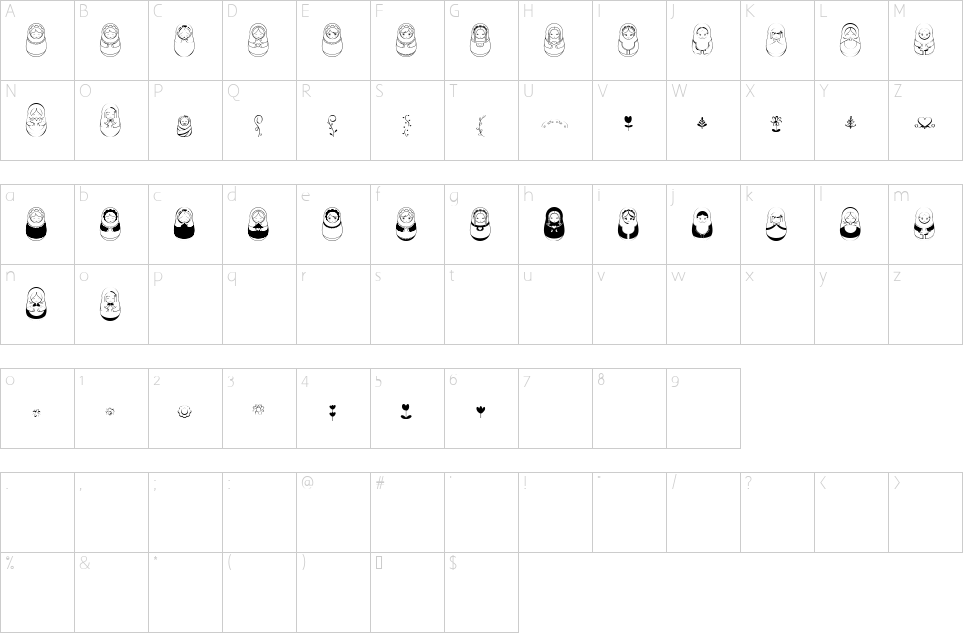
Descubra uma fonte única e elegante chamada Matriochkas que está disponível gratuitamente para download. Matriochkas foi criada por Maelle Keita e já foi baixada 10,455 vezes. Esta fonte adora ser usada em projetos de design gráfico, especialmente para textos de negrito e cursivo. Seja para criar um design gráfico minimalista ou para adicionar um toque de sofisticação a um layout web, Matriochkas é uma escolha perfeita. Se você está procurando por uma fonte moderna para sua próxima peça de design, você não pode deixar de experimentar a Matriochkas. É uma ótima fonte para adicionar uma personalidade única a qualquer projeto.